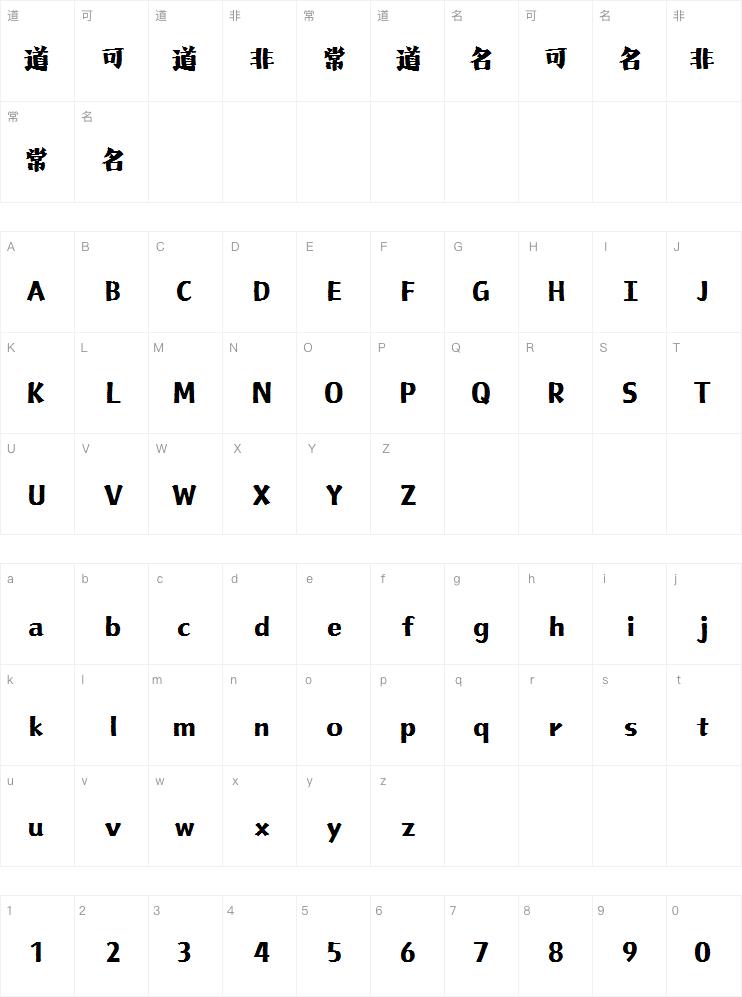
山海脆脆宋,是一款全新的字体,包含汉字9169个,符号200+个。该字体是一款卡通手绘风宋体字体,该字体字形灵动多变,童趣可爱,同时融入手绘风笔画造型,从而使得该字体字形灵动多变,在灵动的同时而又极富俏皮感。在粗细的纵横间,拥有非常规的自由灵动特性。笔画的手绘风效果使字体的气息更加新奇,笔画间的关系密不可分,同时也增加了字体的自由洒脱之感。结构多变灵动,字形活泼清新,造型生动有趣,具有灵活的适用性,天真俏皮又不失时尚感。该字体字形随笔画多少、结构布局不同而大小不一,各个字的大小随字形的不同而呈现不同的大小,但是在变化中寻求平衡,使得整个字体更具有手写感的温度和节奏感,整体笔触圆润。灵动笔画贯穿笔画始终,内涵丰富,弧度柔和,撇笔平缓舒展,尽显俏皮灵动。